השאלון עם שי יוז
הכירו את שי יוז, ילידת 95, מעצבת גרפית שחיה ונושמת טיפוגרפיה, גרידים מדויקים, צבעים עזים ורעש ויזואלי. היא בוגרת המחלקה לתקשורת חזותית במרכז האקדמי ויצו חיפה, ועוסקת במיתוג, פרינט וספרים – ״כל מה שדורש חשיבה קונספטואלית, רגש חזק ואסתטיקה מדויקת". שי מתגוררת ויוצרת בשוק תלפיות שבחיפה עם בן־זוגה צבר, שהוא קופירייטר – "כי לא מספיק אחד אומנותי בבית", ועם אלפי החתול השמנמן. היא מספרת שאין כמו לגור בשוק: "הרעש, האנשים והאווירה, שלא נדבר על הצבעים". כמעצבת, שי אוהבת לקחת את העיצובים שלה עד הקצה. "אין כמו לראות קנבס ריק ולטייל בין אינספור מחשבות ורעיונות שקופצים לי לראש (ADHD כבר אמרתי?)". את המוח הצבעוני שלה היא מתרגמת לעיצוב, ומנגד גם מספרת: "אין דבר שמספק יותר מגריד נקי וטקסטים שמסתדרים בתוכו כמו פאזל". שי מספרת שכשהיא לא עובדת, תמצאו אותה משחקת במשחקי וידאו עם בן־הזוג, צופה שוב ושוב ב־The Office, או מרעיפה על אלפי אהבה, עד שהוא בורח.
היי שי, מה שלומך? איפה אנחנו תופסים אותך השבוע?
השבוע אני עובדת על ספר שבקרוב יראה אור. אני לא יכולה לדבר על זה יותר מדי, אבל זה ספר אדיר!
איפה את עובדת עכשיו?
לא מזמן התחלתי לעבוד בסטודיו מגניב וחיפאי בשם דותן לידז'י. עד כה עיצבתי פוסטרים לסרט, לוגואים ועוד פרויקטים תחת המותג שלי Shyuzz Studio.
על איזה פרויקט מעניין עבדת לאחרונה?
לאחרונה עבדתי על פוסטרים לסרט ישראלי בשם ״מולדת״ של רעות דגבר עג'מי, שאמור לצאת ממש בקרוב.
מה גורם לך להתרגש ולרצות לעצב וליצור?
הצורך להגיד משהו, כשיש לי מה לומר – דרך טיפוגרפיה, קומפוזיציה או צבע.
מה את עושה כשאין לך מוזה?
פותחת Pinterest, שמה פלייליסט של שנות ה־60 או ״המשרד״. מטיילת במחשבות ומערבבת צבעים עד שהיא מגיעה.
מה את עושה בשביל הכיף?
משחקת עם צבר (בן־זוגי) Sea of Thieves ו־Baldur's Gate, מבשלת קארי, ונוסעת לחופשות קטנות כשאפשר.
יש לך הרגל מגונה?
להזיז אלמנטים פיקסל אחד ימינה, ושוב שמאלה, ואז קצת קצת ימינה – וככה עוד אלף פעמים.
הפרויקט עוסק בהרגלים קטנים ושובבים שכולנו מפתחים בתוך השגרה – ההתמכרויות היומיומיות הקטנות שאנחנו אולי מנסים להיגמל מהן, אבל איכשהו תמיד חוזרים אליהן. דרך שפה ויזואלית מלאת הומור, נבנתה סדרה שמצדיעה דווקא לאותם רגעים קטנים, מוזרים, אנושיים. "צ'ירס לאותם הרגלים מצחיקים וביזאריים שהופכים את החיים לקצת יותר מעניינים", אומרת שי.
יצא לך לטייל בחו״ל?
כן, בתור ילדה ההורים שלי לקחו אותי לכל טיול אפשרי, אז יצא שהייתי כמעט בכל אירופה (לא שאני מתלוננת). עשיתי טיול אחרי צבא במזרח, והשבוע אני טסה לסלוניקי עם צבר לקצת מוזה וקפה קר.
תהני! מה משך אותך לתחום?
אהבתי תמיד לשלב בין רעיונות לאסתטיקה. כילדה זה היה דרך איורים, והיום זה דרך מותגים.
תני לנו ציטוט שיעורר בנו השראה.
Don't ever, for any reason, do anything to anyone for any reason ever, no matter what, no matter where, or who, or who you are with, or where you are going, or where you've been... ever, for any reason whatsoever… – Michael. G. Scott
לאן ניסית להתקבל ללימודים ולאן התקבלת?
האמת שלא נבחנתי לשום מוסד לימודים חוץ מויצו, והתקבלתי. 🙂
איזה מרצה השפיע/ה עלייך במיוחד?
פרופ׳ טרי שרויאר האגדית – המרצה שלי לעיצוב. לימדה אותי תעוזה, חשיבה קונספטואלית ואיך לחשוב ולא רק לעצב יפה. ממש ״להרגיש״ עיצוב בכל דבר שאני פוגשת בחיי. היום היא דיקנית הפקולטה לעיצוב.
איזו מעצבת השפיעה עלייך יותר מכל?
Andy Warhol – ההשראה שלי כמעצבת נועזת ובועטת. הצבעים, היצירתיות שלו, המחשבה שמאחורי יצירותיו. עד לרמה שקעקעתי אחת מהיצירות שלו.
במה היית עוסקת אם לא היית מעצבת?
כנראה כותבת, או עורכת ויזואלית של מגזין. במשהו שמשלב רעיונות ואסתטיקה.
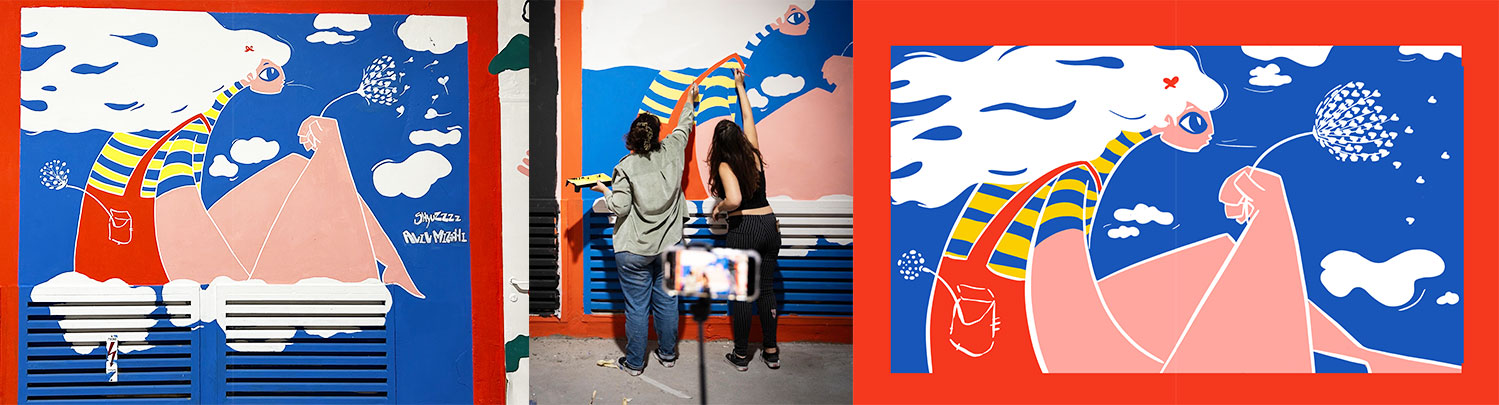
TALKING WALLS הוא פרויקט מוזיאוני־ציבורי בעיר התחתית של חיפה, שבמסגרתו אמנים מקומיים הוזמנו לספר את הסיפור הישראלי על קירות הבניינים. יחד עם אביב מזרחי, שי יוז יצרה דמות עדינה המחזיקה בפרח סביון, שמפיץ את זרעיו ברוח. העבודה עוסקת במעברים בין שבר ותקווה, ומובילה את הצופה למסע רגשי בין זמנים: מימים של שקט ואשליה, דרך כאב וחרדה, ועד רמזים ראשונים לצמיחה. "הסביון שבידיה נישא ברוח, מעין סמל לצמיחה ותקווה חדשה, כאשר מכל זרע קטנטן שיוצא ממנו יצמח פרח חדש", מספרת שי.
רוצה להמליץ על ספר עיצוב?
Grid Systems in Graphic Design של Josef Müller-Brockmann. כל כך מספק לכל מי שאוהב סדר, היררכיה וגרידים. הוא מזקק את מהות העיצוב ונותן כלים שעובדים בכל שפה וסגנון.
באיזה פונט את רוצה שיכתבו על המצבה שלך?
קראוון של אאא הוא בדיוק השילוב שאני אוהבת – יש בו אופי, נוכחות, גרוב, אבל גם רוך ודיוק. הוא מצליח להיות נוסטלגי וחדש באותו זמן, בועט אבל מחושב. כמוני 🙂
יש לך המלצה מוזיקלית?
כל שיר של The Beatles.
מהי משמעות החיים?
צבעים ואהבה.
איך עולם העיצוב ייראה בעוד עשור?
אני ממש מקווה שיותר צבעוני ומסודר מהיום.
מה שם החיבה שלך?
שייקי או שיוז.
קיצור מקלדת אהוב?
Cmd + Z. החיים היו הרבה יותר קריטים בלעדיו.
כתבי בבקשה את המילה הבאה בכתב היד שלך: